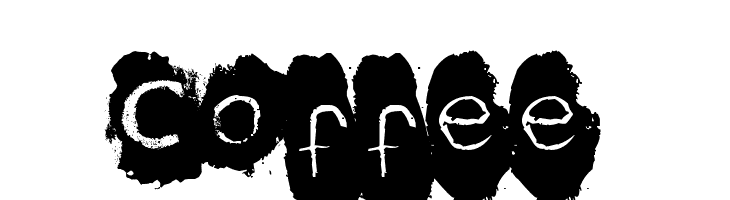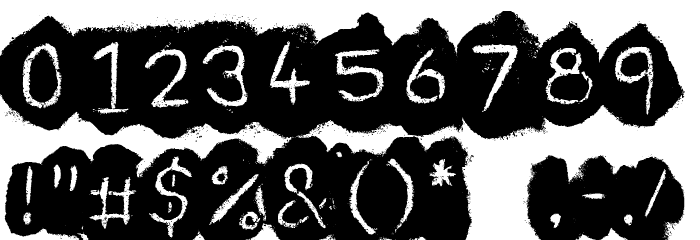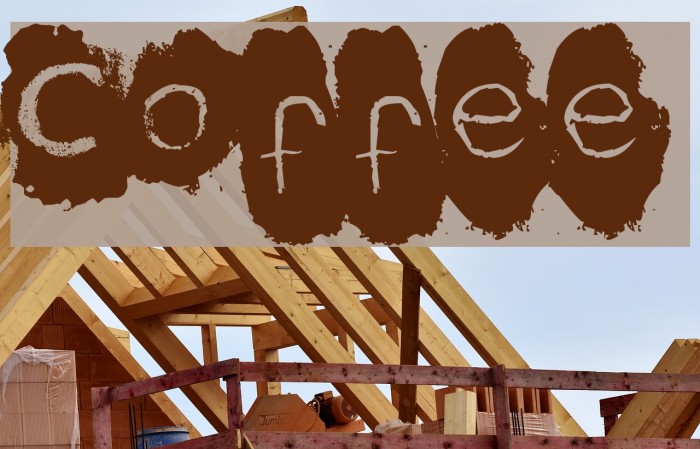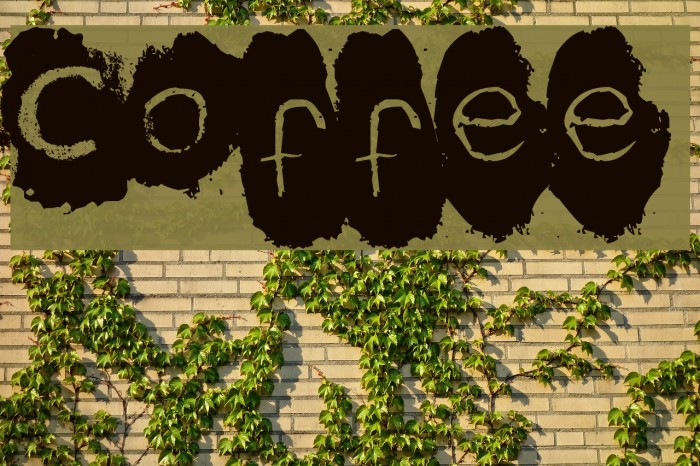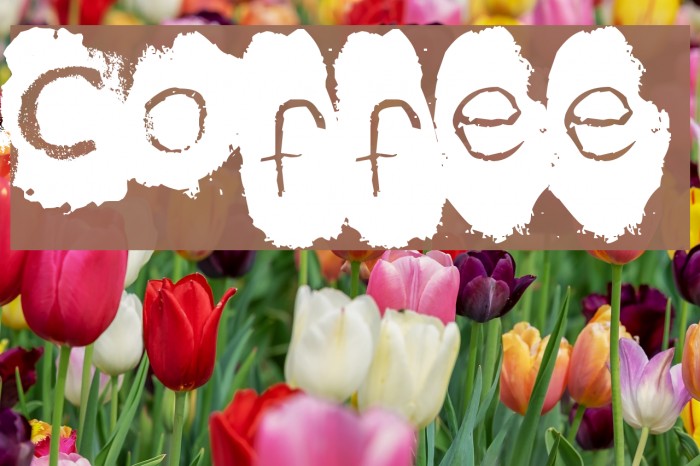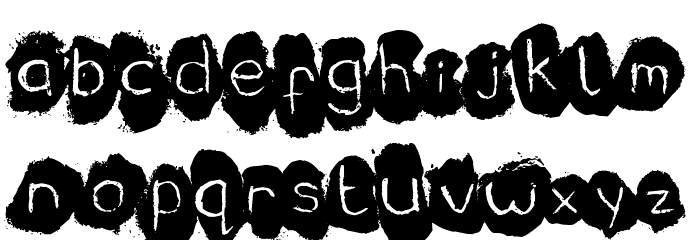
Coffee Font
| Gesamtstil | Casual, Artistic |
| Anwendungsfall | Logos, Posters, Branding |
| Vorgeschlagene Projekte | Ideal for cafe branding, playful posters, children's book covers, and creative social media graphics. |